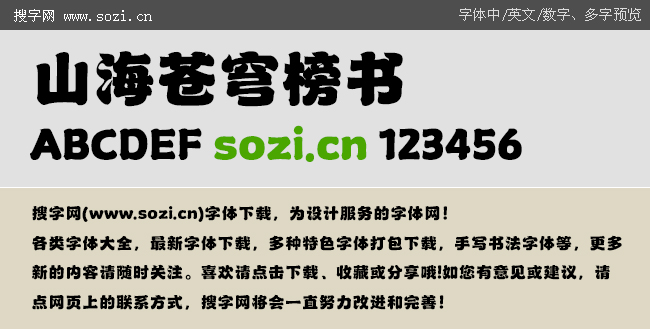
山海蒼穹榜書(shū)
搜字網(wǎng)提供一款山海蒼穹榜書(shū)中文字體下載,山海蒼龍榜書(shū)是一款手寫(xiě)風(fēng)格的毛筆字體。榜書(shū)古時(shí)又稱(chēng)作署書(shū),是書(shū)寫(xiě)在匾額上的大字,山海蒼穹榜書(shū)字體粗壯有力,字形端莊大氣,視覺(jué)效果非常不錯(cuò)。適合標(biāo)題設(shè)計(jì)、海報(bào)設(shè)計(jì)、廣告設(shè)計(jì)等應(yīng)用。